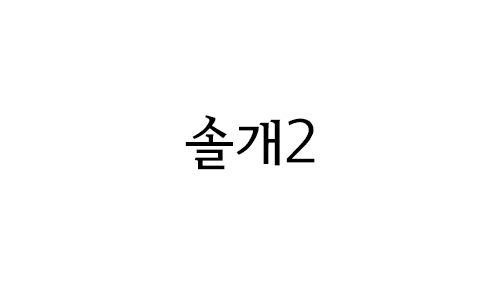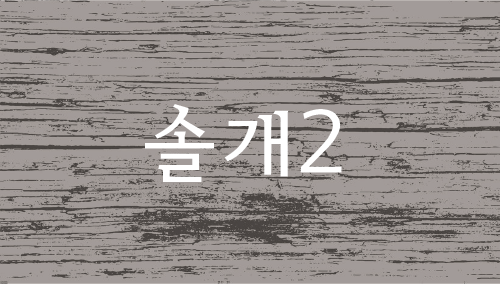
#본문HU솔개2
폰트      HU솔개
굵기      2종
기간      2009
구성      KS한글 2,350자
KS특문 986자
영문 94자
한글과 영문의 조화와 자간이 조정된 솔개의 업그레이드된 서체입니다.
HU솔개220
오랫동안 꿈을 그리는 사람은 마침내 그 꿈을 닮아간다.
HU솔개240
오랫동안 꿈을 그리는 사람은 마침내 그 꿈을 닮아간다.